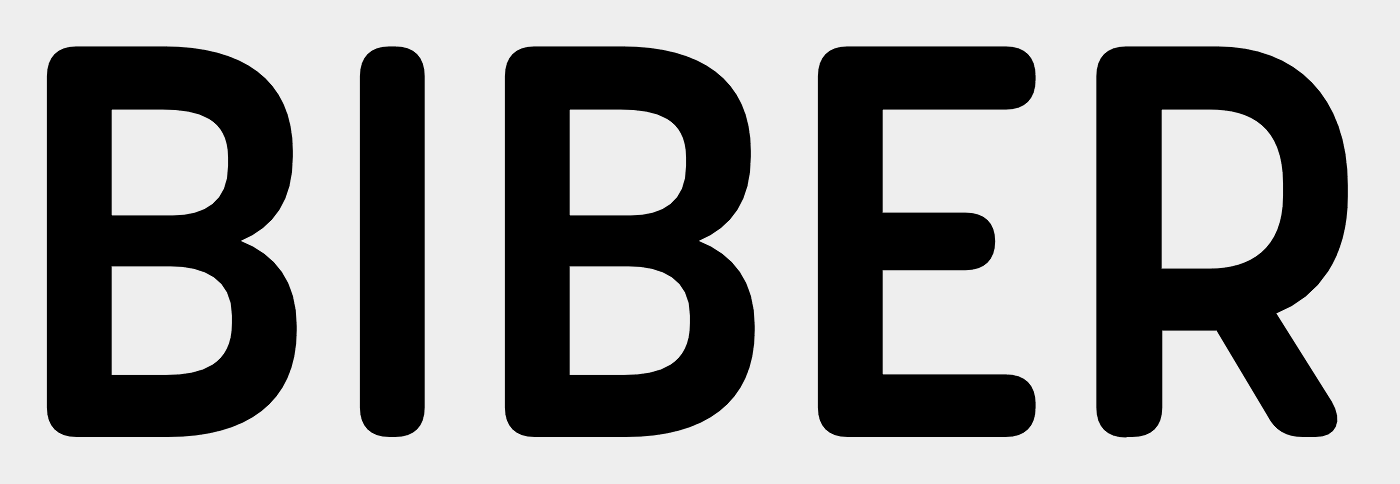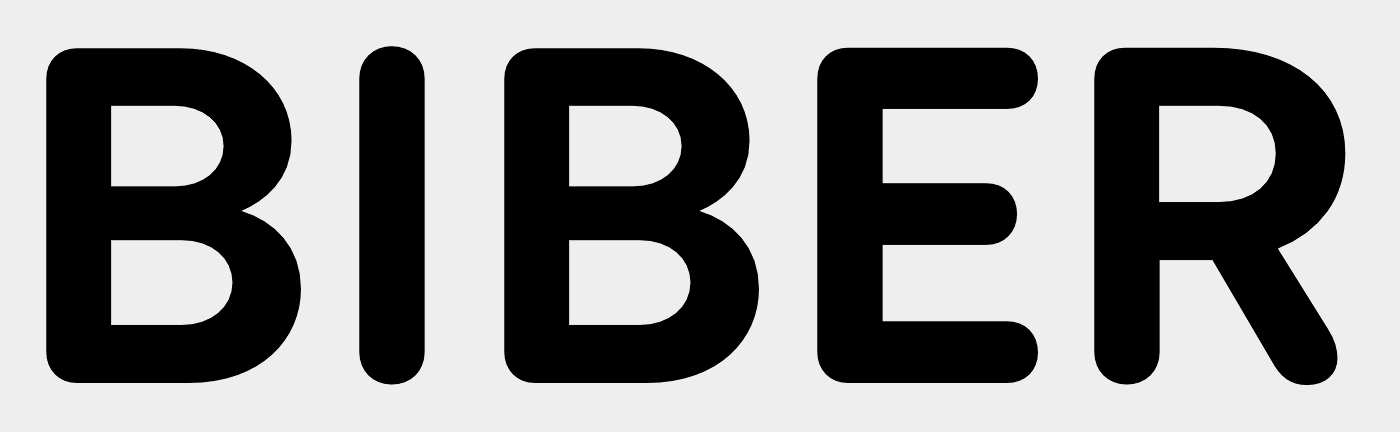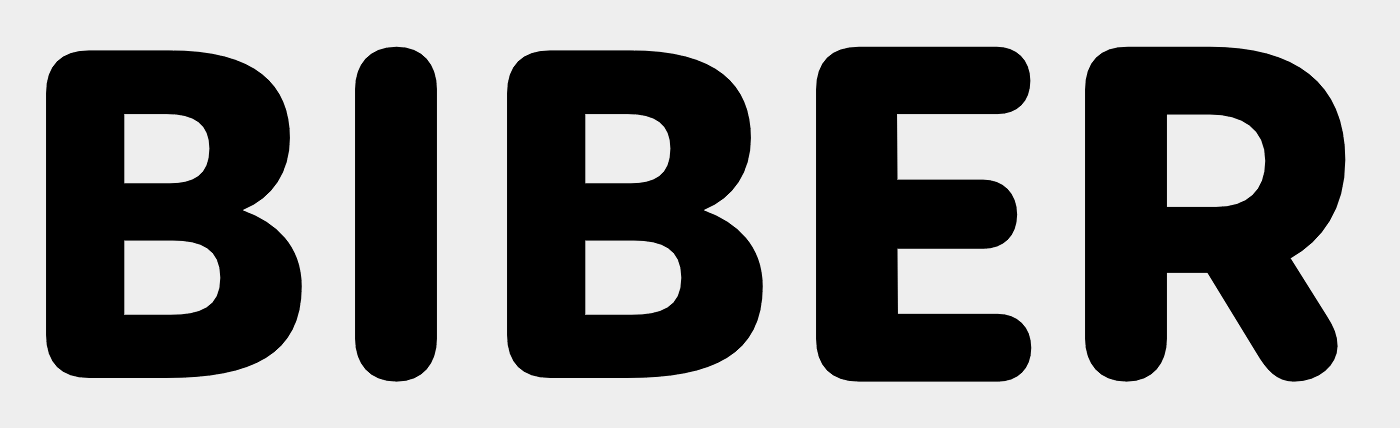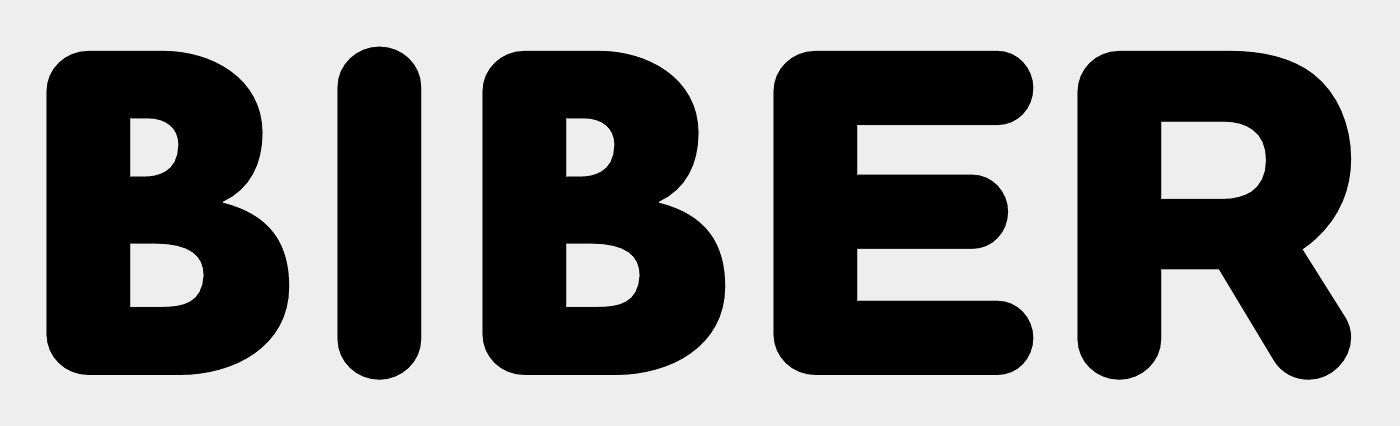
Suche Schrift von den Seeländer Biber Freunde
Für den Verein Seeländer Biber Freunde möchte ich das Logo wiederherstellen. Momentan ist nur ein jpg Bild vorhanden und wir benötigen das Logo als vektorisierte Datei. Weiss jemand was für eine Schrift verwendet wurde?
Das Logo wirkt ehrlich gesagt sehr unausgegoren auf mich. Das beginnt schon bei der Schriftwahl. Wollt ihr die Gelegenheit nicht  nutzen und es gleich etwas optimieren?
Als Font würde aus meiner Sicht zur Grundform des Bibers zum Beispiel so etwas besser passen:
ich stimme R::bert zu: Die Bildmarke Eures Logos ist wirklich schön und ansprechend! Der umrundende Schriftzug wirkt in Relation dazu recht brachial. Wenn es möglich wäre, da eine ansprechende Schriftalternative zu wählen, die den Duktus der Bildmarke besser aufgreift und dieser in der Aufmerksamkeitshierarchie den Vortritt ließe, dann würde das Logo noch mal deutlich gewinnen. Die Schriften, die R::bert vorschlägt (Impact-Alternativen), eignen sich für meine Begriffe wirklich gut, diese Richtung würde ich auch empfehlen. :-D
Ja, aber auch die Alternativen finde ich für diesen Einsatz nicht optimal. Sie sind mir zu kompakt oder zu technisch. Bei einer Überarbeitung des Logos würde ich auch die Schriftfarbe ändern, damit die Bildmarke nicht so sehr in den Hintergrund gedrückt wird.
Das und einiges mehr.
Wenn's denn unbedingt mit Serifen sein muss: http://www.identifont.com/similar?28C8
Damit Maisfeld sich in der Richtung der jetzigen Schrift weiterorientieren kann, hatte ich auch auf Identifont (Alternativen zur Aachen) verlinkt. Ich denke aber wie R::bert, dass ein Schriftstilwechsel sinnvoller wäre.
Och, außer Maul und Schwanz (ich würde gleichmäßige Strichstärken vorziehen) würde ich an der Bildmarke gar nichts ändern. Aber egal, welche Schrift schließlich gewählt wird, muss sie ausgeglichener umlaufen. Die Buchstaben- und Wortabstände sollten auf jeden Fall besser zugerichtet werden. Da ist noch einiges zurechtzuzupfen – einfach Text auf einen Kreispfad laufen lassen genügt nicht.
Tatsächlich so verallgemeinernd?! Einige ja. Aber ich sehe da auch durchaus denkbare Kandidaten wie die zum Beispiel:
Mit der Korelev habe ich keine guten Erfahrungen gemacht. Da sind mir zumindest einige Schwachstellen in Erinnerung. Bei der Houschka finde ich die Buchstabenbreiten sehr unausgewogen, zum Beispiel wirkt das B auf mich zu schmal bzw. E und R zu breit, aber das nur am Rande …
Vielleicht habe ich mich allzusehr an der Kopfform des Bibers festgebissen. Die von mir genannten Rounded-Schriften, hab ich nicht alle in meinem Fontköfferchen. Es war also mehr ein Aufzeigen, was ich wählen würde. Damit war keine Empfehlung in technischer Hinsicht verbunden. Aber es ist immer gut, wenn jemand die Schrift schon eingesetzt hat und auf Mängel hinweist, die man ja meist erst zu spät (nach dem Kauf) bemerkt. Den Tipp zur Korelev werde ich mir merken. Danke dafür.
Die Colfax gefällt mir. Man müsste einfach mal Entwürfe sehen. Dazu muss Maisfeld aber erstmal äußern, in welche Richtung es gehen soll.
Ich bin bei den Rounded-Vorschlägen etwas skeptisch und hatte sofort einen schwedischen Rucksack im Kopf ... aber vielleicht passt es ja auch.
Was wäre denn mit Schriften wie der Heroic oder anderen condensed-Schriftarten? Oder alternativ so etwas wie Clan oder Gotham? Sorry, rotiere gerade arbeitstechnisch und kann die entsprechenden Schriften nicht direkt verlinken …
ich fände es toll, wenn die Originalschrift identifiziert werden würde. Die Form der Serifen am S und der Fuß des R sowie dem A ohne Balken oben habe ich so in keiner Schrift als Kombination gefunden. Reine Neugier ...
Ich schließe mich dem allen – außer Index – nicht an! Eine Sans oder sogar Rounded würde ein gänzlich anderes Gesamtbild schaffen … Die dicken Serifen finde ich gut und der Bruch zum Zeichen finde ich auch okay. Allerdings könnte man in der Tat alles etwas anpassen – Spationierung, Kerning, vielleicht ein etwas hellerer Schriftschnitt oder einfach nur kleiner :-?
Ich finde eine dermaßen schwere Slab auch deshalb schwierig, weil sie die kreisförmige Grundlinie mit ihren dominanten Serifen zu einem holprigen, unregelmäßigen Vieleck macht. Das beißt sich ja schon sehr mit der Figur und dem Kreis darum, auf den mit der Grundlinie ein unmittelbarer Bezug hergestellt wird. Bei den vorgeschlagenen Serifenlosen fiele das nicht so auf, bei den Rounded-Kandidaten sogar noch weniger. Aber Slab auf Kreis? Eher schwierig.
Schrift und Bildmarke bilden einen Kontrast, das ist richtig. Es ist nur die Frage ob man den aufgeben oder harmonisieren sollte :-?Ich hielte eine Rounded für viel zu weichgespült … m2cent
Viele Wege führen nach Rom oder auch zu einem guten Logo. Man müsste einfach mal verschiedene Entwürfe sehen. Dann könnte man sich konkreter äußern. Ich fürchte aber, dass der Threadöffner nach der löblichen Identifizierung durch Index hier nicht mehr mitmacht.